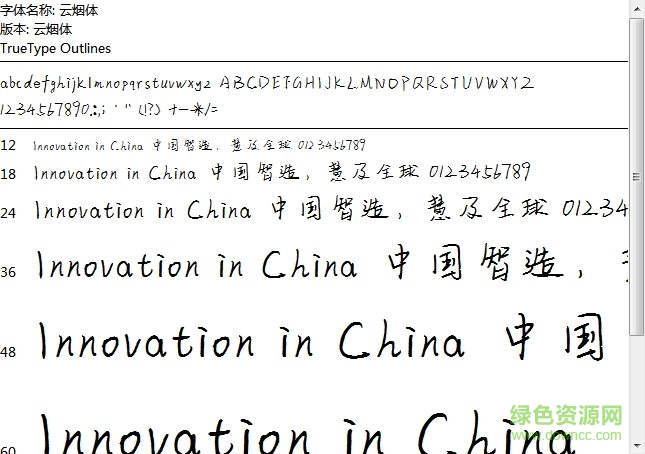
云煙體ttf筆畫清爽而圓潤,不是中規(guī)中矩的橫撇豎直之態(tài),更顯得溫和與灑脫,擁有極佳的視覺好感,讓文字蘊(yùn)含著古風(fēng)的韻味,喜歡的朋友就來綠色資源網(wǎng)試試吧!
云煙體自己柔和而不是飄逸,干凈簡潔而不含凌亂,書寫十分嚴(yán)謹(jǐn)而溫潤。
云煙體是一款大家找了很久的藝術(shù)字體,分享出來讓大家的藝術(shù)設(shè)計(jì)更有增色,作為一款硬筆手寫字體,干凈而不尖銳給人感覺良好。